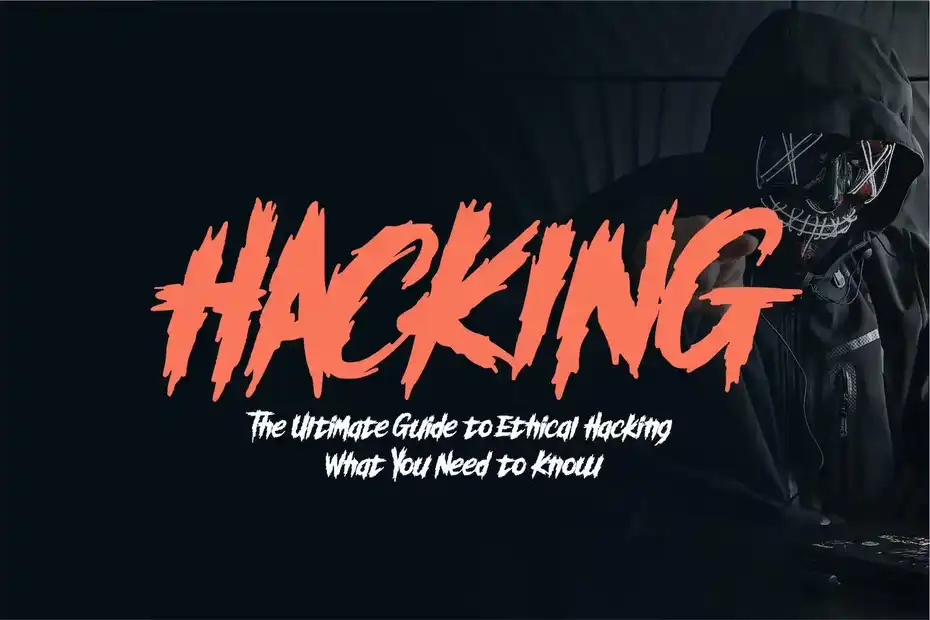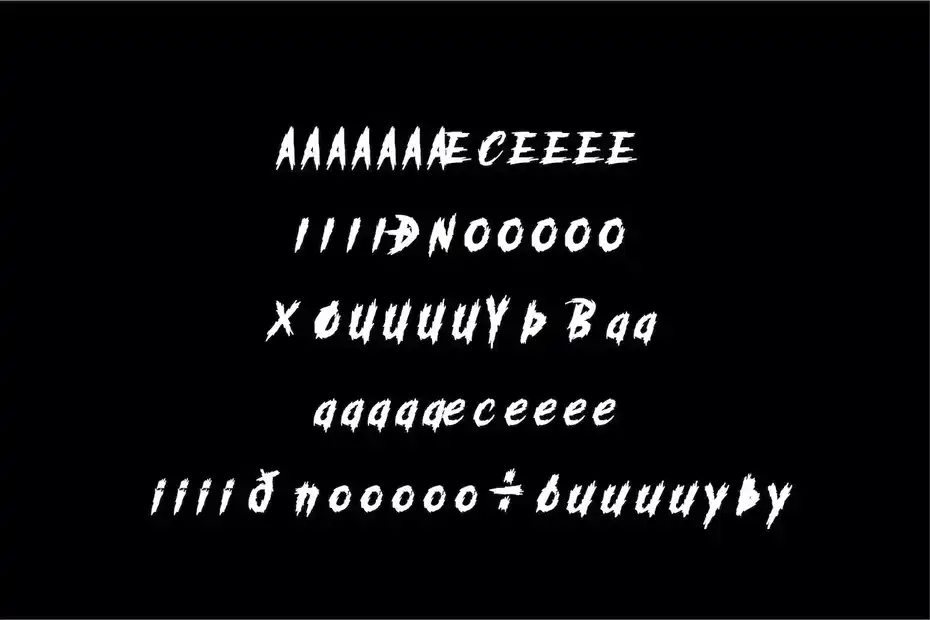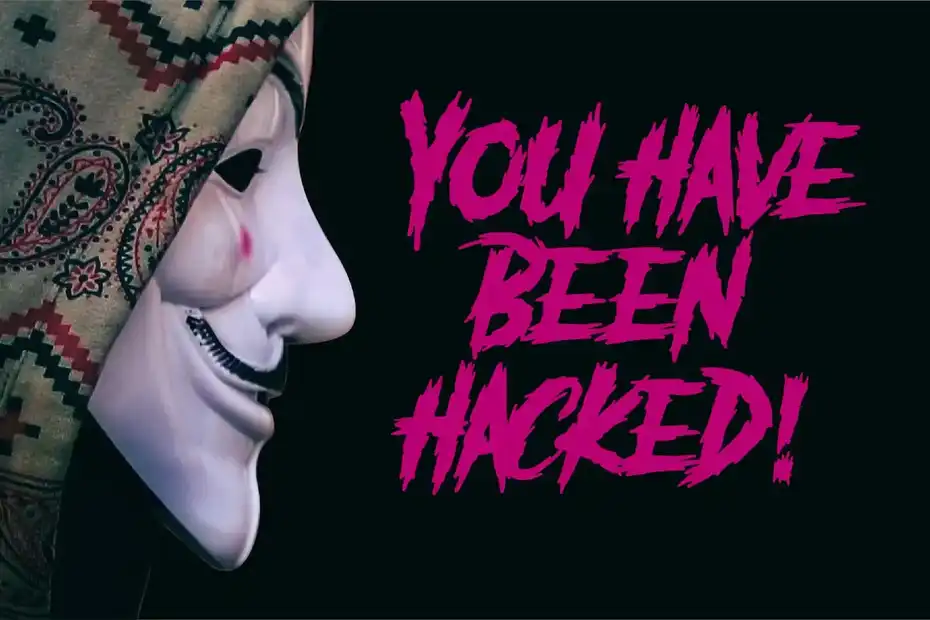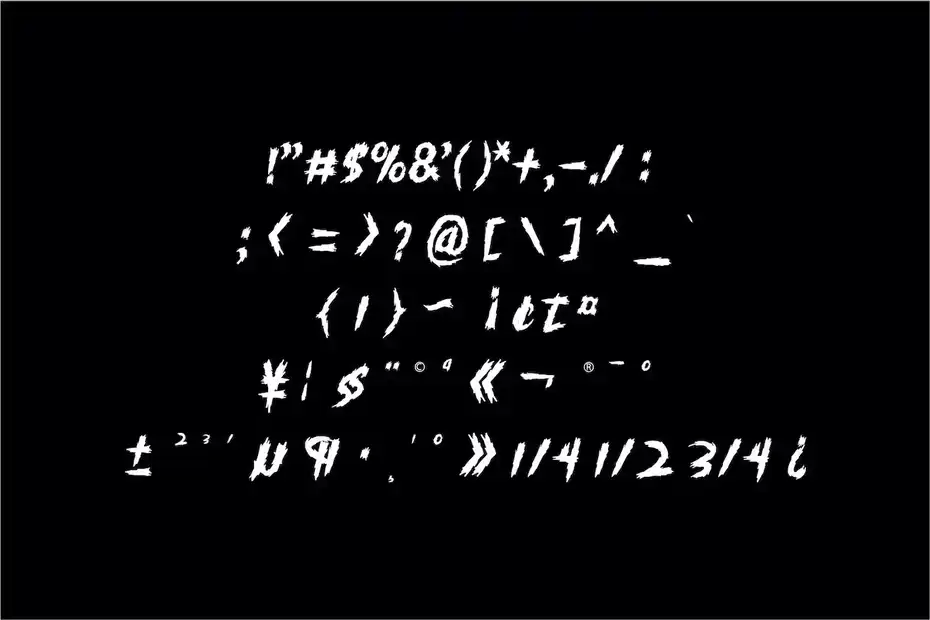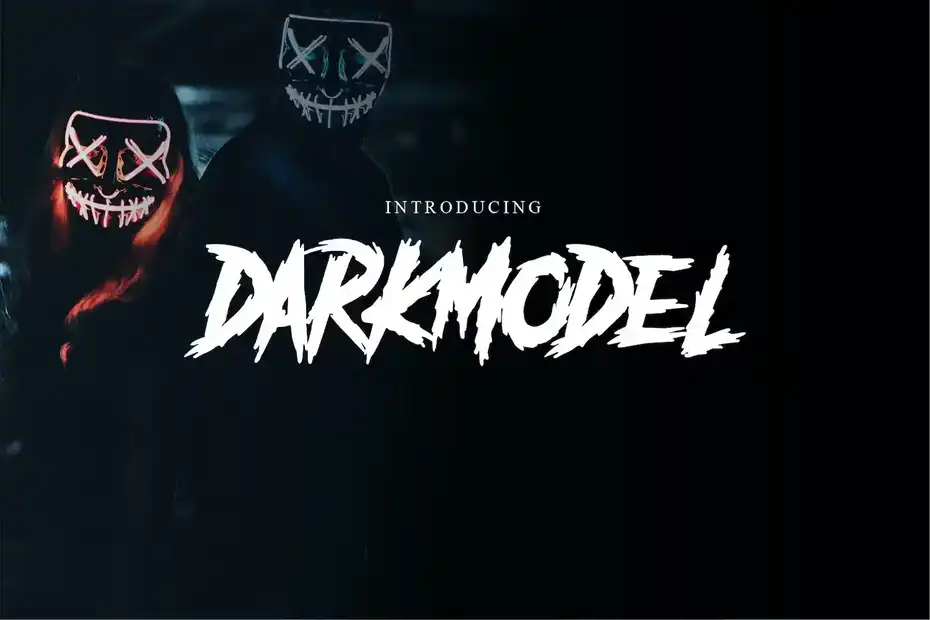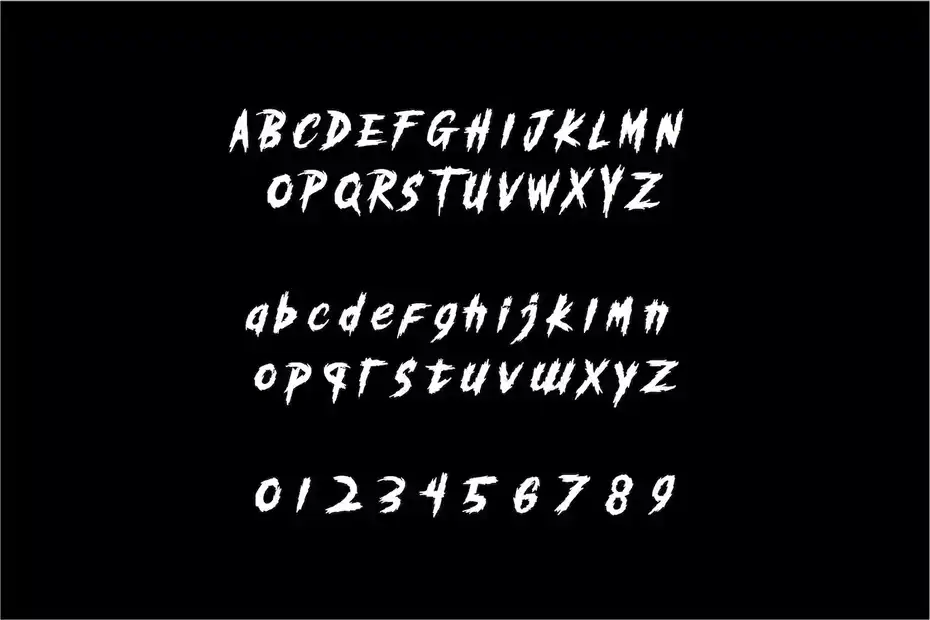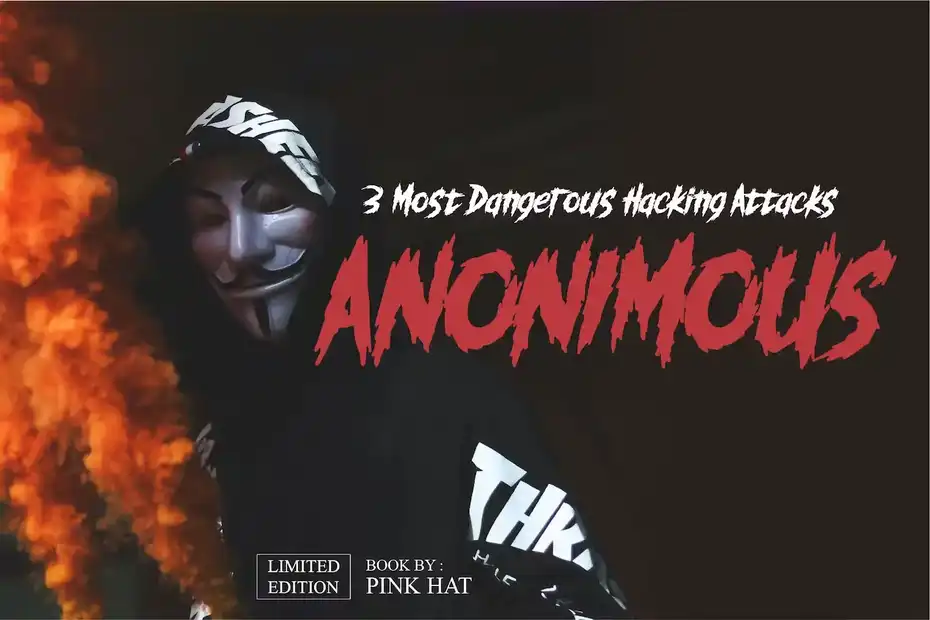
دانلود فونت انگلیسی ترسناک Darkmodel Horror Gothic Typeface
فونت انگلیسی ترسناک Darkmodel Horror Gothic Typeface : این مجموعه شامل یک فونت انگلیسی ترسناک است که برای لوگو، فیلم، نقل قول، جلد کتاب، تایتل، کاور آلبوم، دعوت نامه، رویداد، برچسب، پوستر و غیره مناسب میباشد.